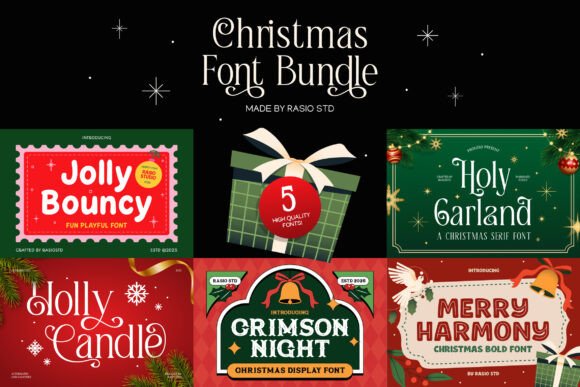
Christmas Bundle
Christmas Bundleのような高品質の素材をお探しの場合、このプレミアムパッケージはクリエイティブなプロジェクトに素晴らしい選択です。
精密に作られたChristmas Bundleは、クリーンなベクター、滑らかなタイポグラフィ、そして安心のための商用ライセンスを提供します。
POD(オンデマンド印刷)製品、結婚式の招待状、またはソーシャルメディアのグラフィックを作成している場合でも、Christmas Bundleは理想的です。